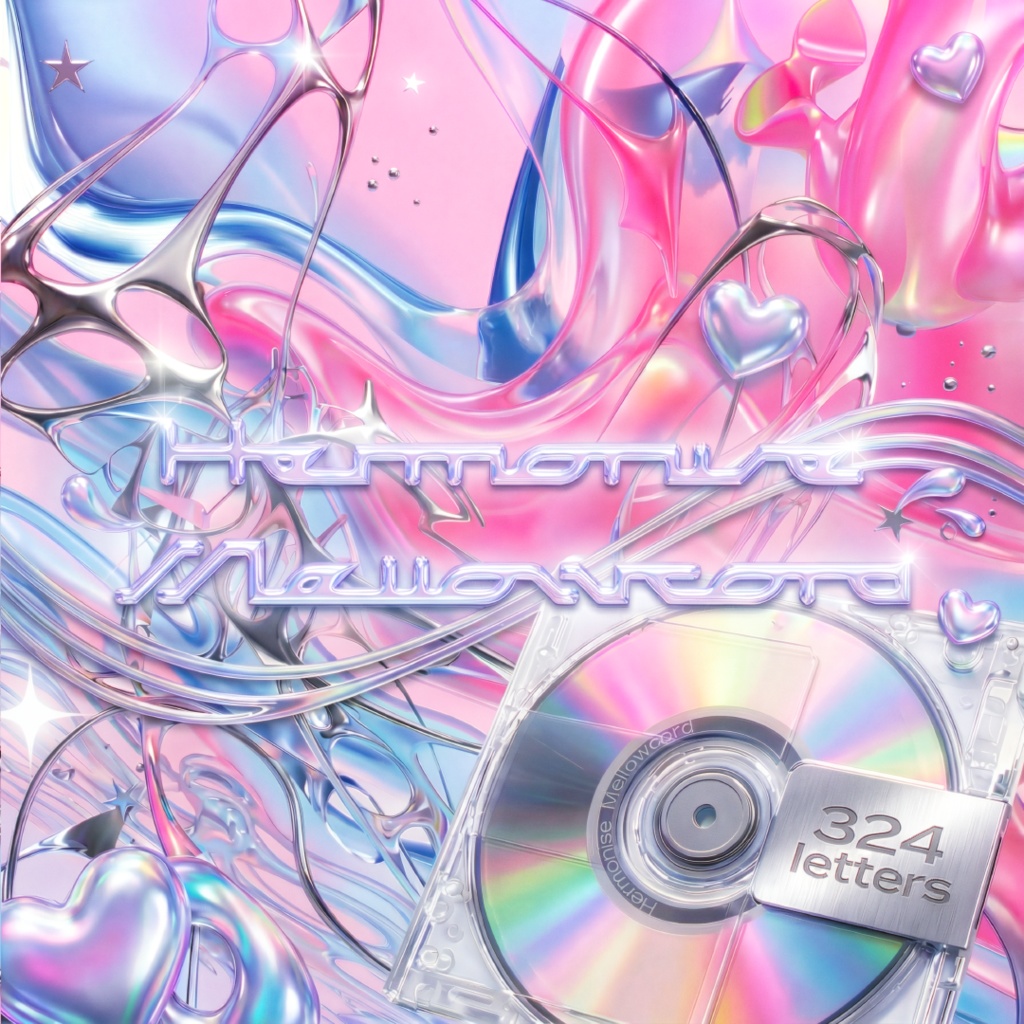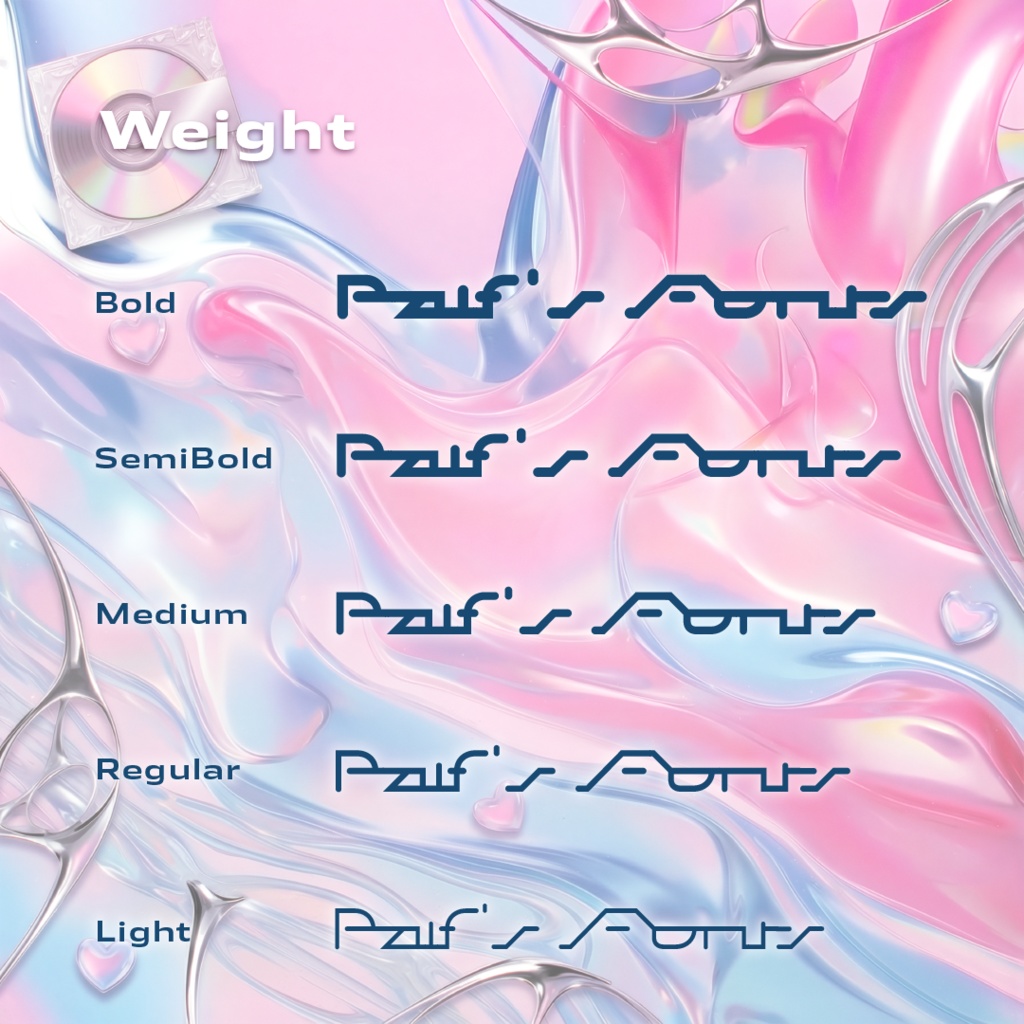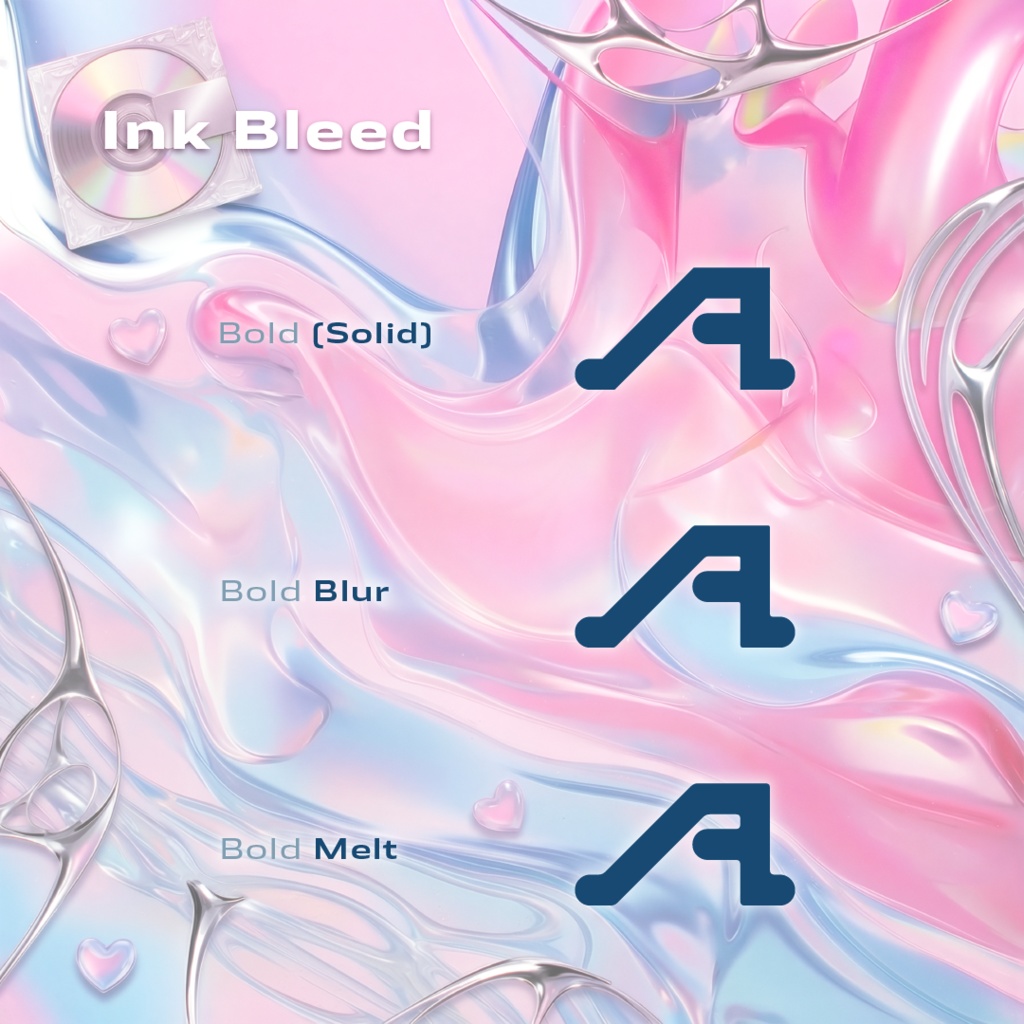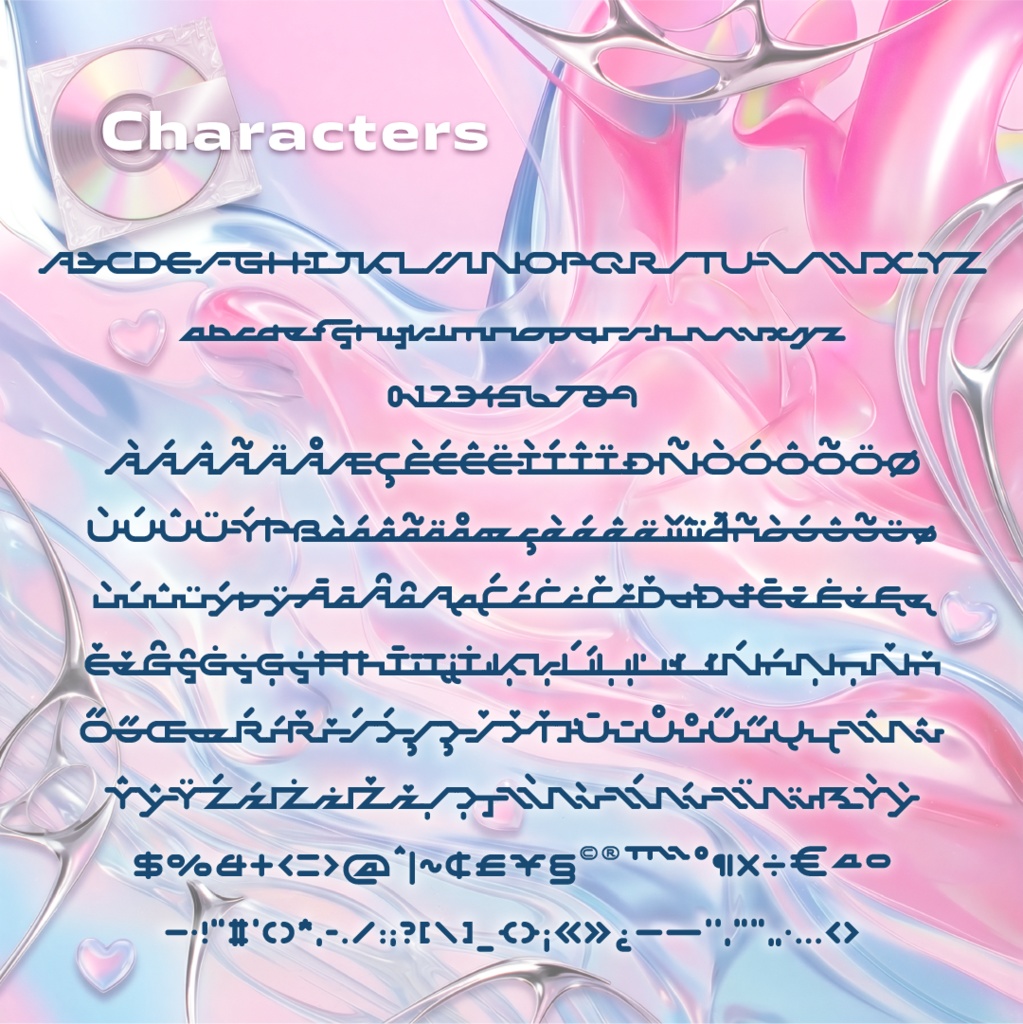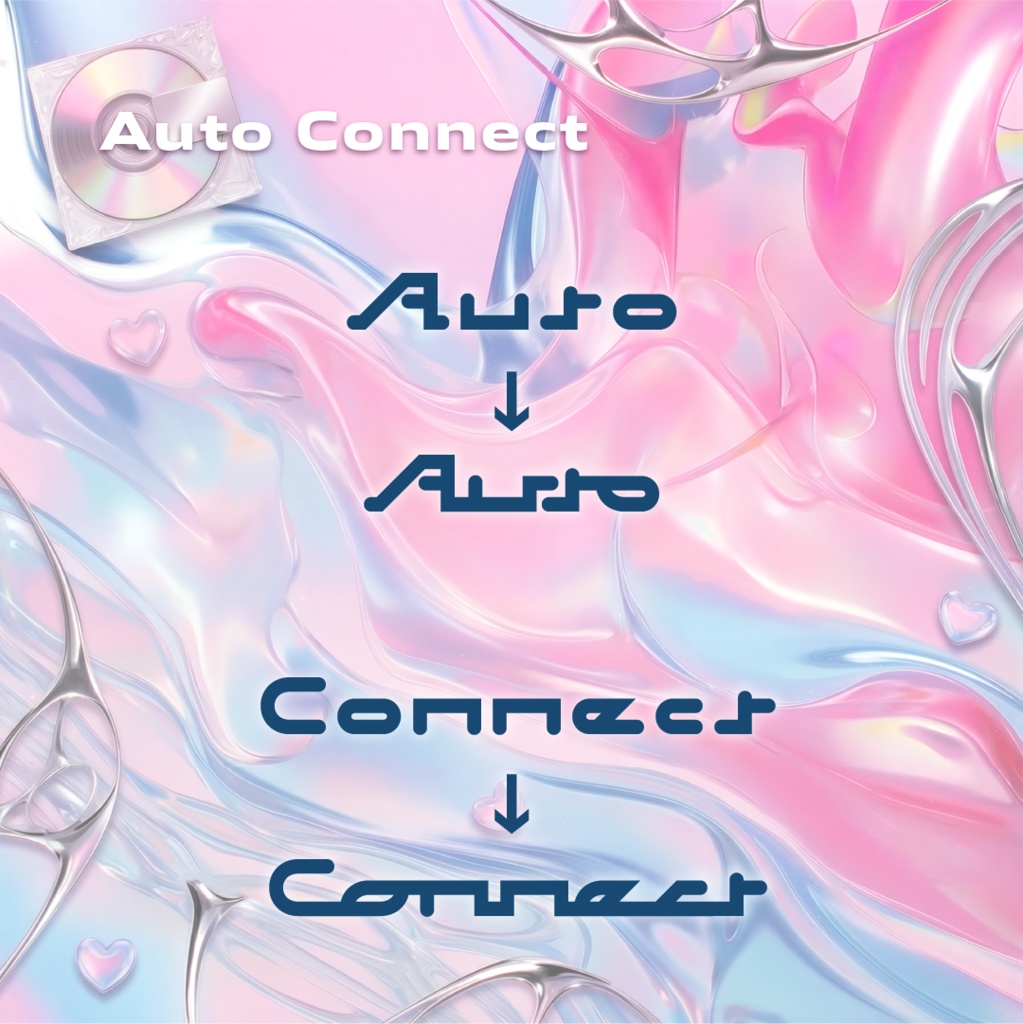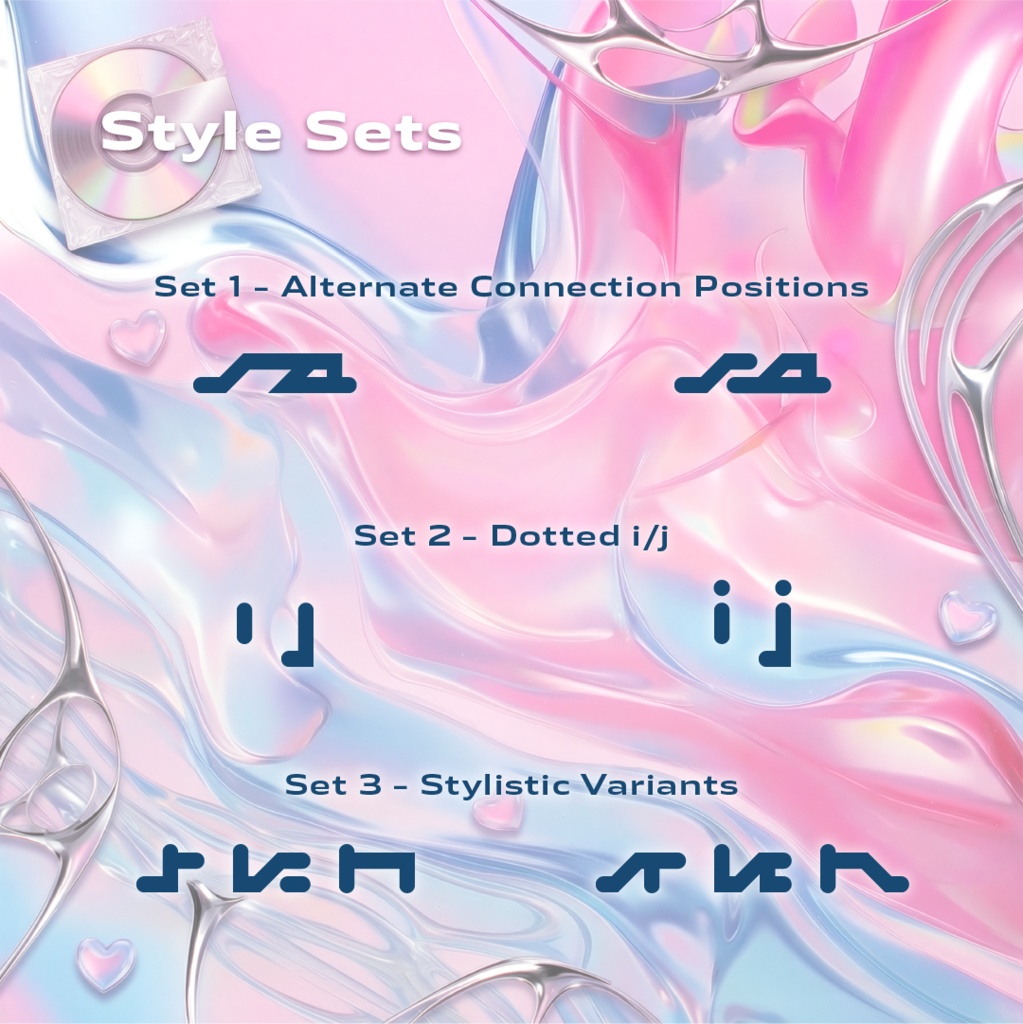
HarmoniseMellowcord【フォント】
入力すれば自動で文字が繋がるフォント Y2Kっぽさのある無機質だけど可愛いデザイン 5ウェイト + 墨溜まり強度3つの計15スタイル フルセットではおまけでバリアブルフォント版が付属します! *OpenType機能のcaltが機能する環境に限ります。Illustratorでは機能しますがAfterEffects上では機能しませんでした。 【フォント仕様】 ・収録文字種 GF Latin Core 2,097グリフ/324文字 収録 OpenType / TrueTypeフォント 【利用規約】 当フォントをご利用された時点で、この利用規約に同意したものと見做します。 当フォントデータは、本規約に定める条件でご利用者様に使用する権利を許諾します。 当フォントの著作権やその他一切の権利はPalfに帰属します。 ●使用条件 1) 2人以上の複数人でご利用になる場合のみ、1ライセンスにつき端末3台までといたします。 2) 本フォントを使用して得られる結果については、仕様者自身が責任を負うものとします。 3) 一般印刷物の作成(ポスター、書籍、フライヤー等)にご利用いただけます。 4) 立体制作物の作成(ステッカー、Tシャツ、アクリルキーホルダー等)にご利用いただけます。 5) 映像及びWebに関連する制作物に於いては、画像化・アウトライン化した上でご利用いただけます。 6) ロゴマーク、タイトルデザインの作成にご利用いただけます。 7) 画像化・アウトライン化したものを加工・変形してご利用いただけます。 8) 購入者本人又は事務所内等での限定した使用に限り、当フォントファイルを改変し、本人のみが使用することができます。 ●禁止事項 当フォントファイルを使用する際、以下の事項を禁じます。 1) 第三者への譲渡・貸与・配布・販売 2) 当フォントデータを元とした、類似又は同一フォントのデータの作成 3) 公序良俗に反する目的、誹謗中傷目的での使用 4) 政治的・宗教的利用 5) 犯罪への利用 6) 当フォントのサーバー上へのアップロード 7) 当フォントデータを取り出すことができるソフトウェアへの組み込み ●その他 ・上記に記載されていない事項については、著作権法及び関連法規に従うものとします。 ・本利用規約は予告なしに変更されることがあります。